良質なデザインを作るには、良いフォントが欠かせません。
それでは、「良いデザイン」ってなんでしょう?
ちょっと頭に思い浮かべてみてください
例えば…
・かわいいデザイン?
・お客さんが使いやすいデザイン?
・意味が伝わりやすいデザイン?
こんな感じでしょうか?
じゃあ正解の発表です
正解は…
全部です!
というかデザインの正解は、状況によって変わるんですよね
なので、状況によって変わる「いいデザイン」に対応するためには「たくさんの種類のフォント」が必要になります
たくさんの種類のフォントで、表現の幅を広く持つことで、デザインを正解に導きやすくなります
この記事はデザイナーだけではなく
・イラストレーター
・エンジニア
・ブロガー
・プレゼン資料を作っている人
・学校やサークルでチラシを作る人
このような人たちに役立つ、フォントの使い方講座です
世の中に「具体的なフォントの使い方を説明している本」が少ないのは、フリーフォントばかり紹介してしまうと有料フォントが売れなくなるからです
有料フォントはハイクオリティですし、フリーフォントより一括ダウンロードができて便利だったりします(手間も少ない)
でもね、無料でもある程度デザインはできるんですよ
しかもここ数年、日本語フリーフォントのレベルはかなり上がっています
もしデザインがうまくなりたいと思っているのなら、今回紹介するフォントを手に入れてからデザインを作ってみてください
表現方法がたくさんあるとデザインの幅が広がります
良質なデザインを作るため揃えるべきフリーフォント
どんなフォントを持っていると様々な種類のデザインに対応できるのか、事例付きで紹介していきますね
1.マルチに使える基本フォント3つ
まず使用頻度の高いフォントは
・ゴシック体
・明朝体
・丸ゴシック
です
本文、タイトル、なんでも使えます
「自分のパソコンにはゴシック体入ってるから必要ないよ!」
と思った方も、この良質なゴシック体を使ってみてほしいです
パソコンに最初から入っているフォントより表現方法の幅が広がります
1-1 フリーフォントで良質なゴシック体はコレ!
Noto sans(ノトサンズ)
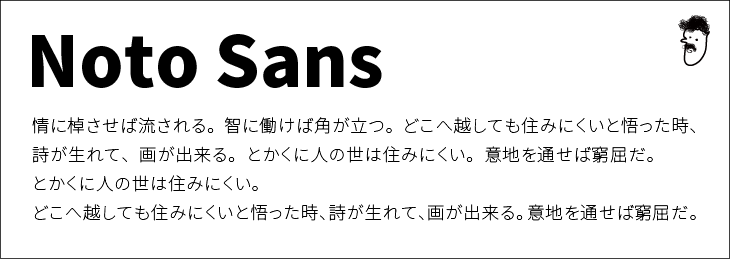
まず紹介したいのが、通常のゴシック体Noto sansです(別名:源ノ角ゴシック)
PhotoshopのアドビとGoogleが一緒に作ったフォントですね
Windowsにはメイリオ、Macにはヒラギノというキレイなゴシック体も入っていますが、Noto sansとなにが違うかと言うと
太さが7種類もある
これはデザイナーには当たり前ですが、一般の人には知られていないものすごく重要なことです
太さが7種類あるフォントだとどんなことができるか、ここから説明していきますね
ロゴの記事でも書きましたが、誰でも使える簡単で強力なテクニックの1つに「強弱をつける」というものがあります
この例を見てください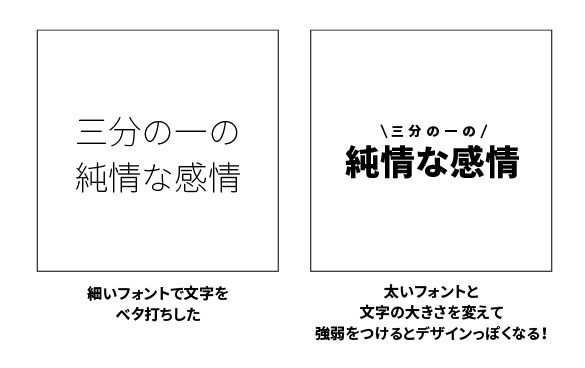
同じゴシック体でも、太さが違うとまるで別のフォントです
そしてこんなに太いフォントは最初からパソコンに入っていません
たくさんの太さがあるフォントを持つことで、表現方法が多様になりデザインの幅が広がります
▼Noto sans(ゴシック体)の使用方法
・タイトル文字
・本文
・ロゴなど文字を加工する前の骨組みとして
基本のフォントなので、何にでも使える汎用性があります、太ければ力強さを表現できるし、細いとおしゃれなデザインにも使えるマルチなフォントです
(例)
同じような文字の使い方で「力強さ」「おしゃれさ」を表現しました
・力強さを出すためには、太い文字と画像でなるべく白と黒の差を出す
・おしゃれを表現するためには余白を大事にする
ことを意識しています
▼こんなYouTubeやテレビのテロップも太いゴシックで作れます
ゴシック体の応用編
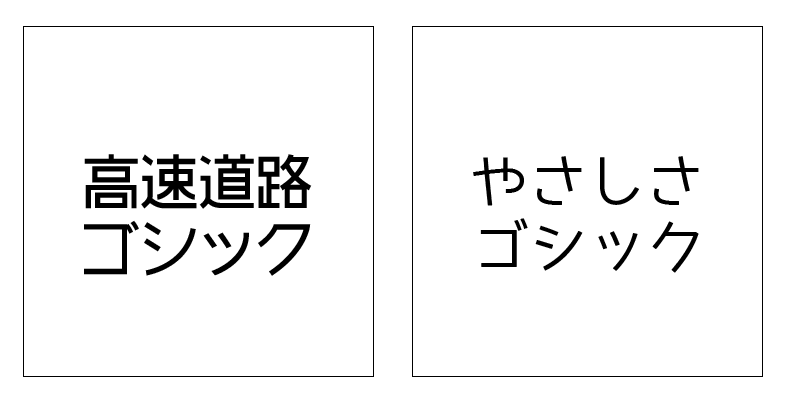
フリーフォントには他にも特徴的な楽しいゴシック体があります(太さはないけれど…)
例えば、
・高速道路ゴシック
・やさしさゴシック
こちらもゴシック体の仲間ですが、特徴的なフォントなので、使い方としては「3.デザインの質を上げる!デザイン系フォント」をご覧ください!(下の方です)
1-2 良質な明朝体
こちらで紹介するのは、ゴシック体と同様、定番のフォント「明朝体」です
紹介するフォントも、先程のGoogleとアドビが作ったフォントの明朝体バージョンです
Noto serif
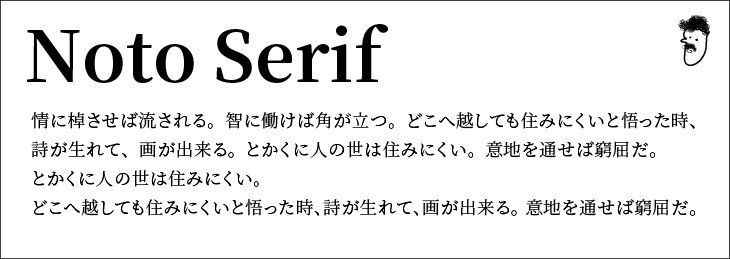
こちらも太さが7種類あるおかげで、さまざまな表現方法があります
▼Noto serif(明朝体)の使用方法
・タイトル文字
・本文
ゴシック体と違って、堅い雰囲気や、おしとやかな雰囲気を出しやすいです
新聞の文字は明朝体ですが、すべての文字がゴシック体になったら…子供向けな感じで理解しやすい雰囲気の媒体になる気がします
▼ポスターっぽい事例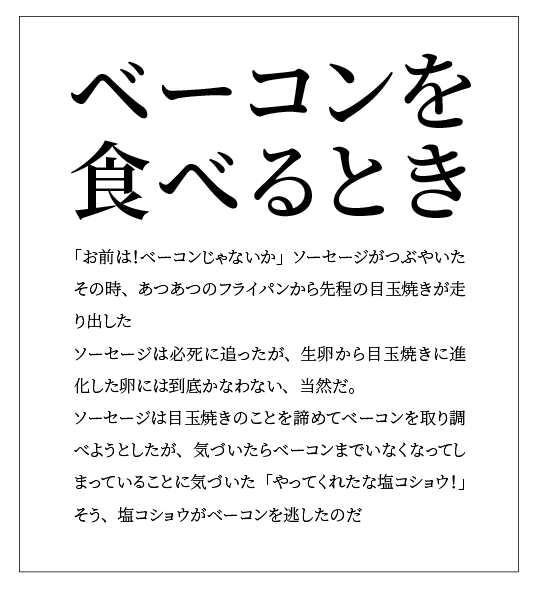
ポスターを作ってみました
・タイトルが太い明朝
・本文が細い明朝体
になっています
タイトルを細い明朝にするとこんな感じ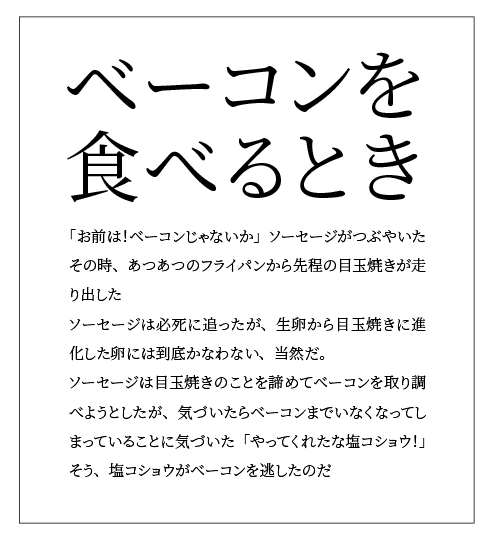
太いフォントがあると便利です
1-3 良質な丸ゴシック(フリーフォント)はコレ!
続いてみんな大好きな丸ゴシックです
源柔ゴシック
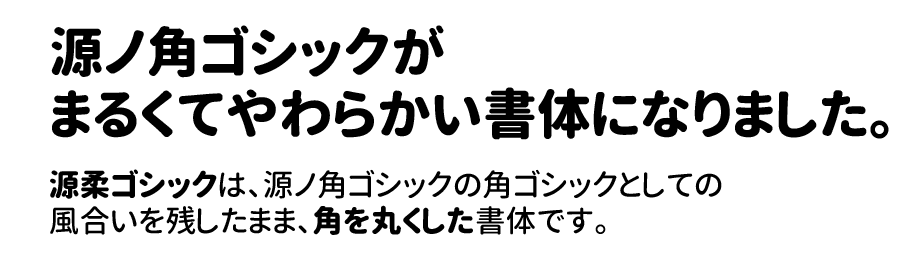
Noto sans(別名:源ノ角ゴシック)を角丸にしたフォントです
柔らかくて女性的なイメージでも使いやすいフォントです
こちらのフォントのいいところは、もうわかりますよね?
そう、太さが7種類あるところです!
さあ、ここから事例です、まずはこちら
これは、無料画像ソフトCanvaで作った画像です、文字の太さはHEAVYを使っています
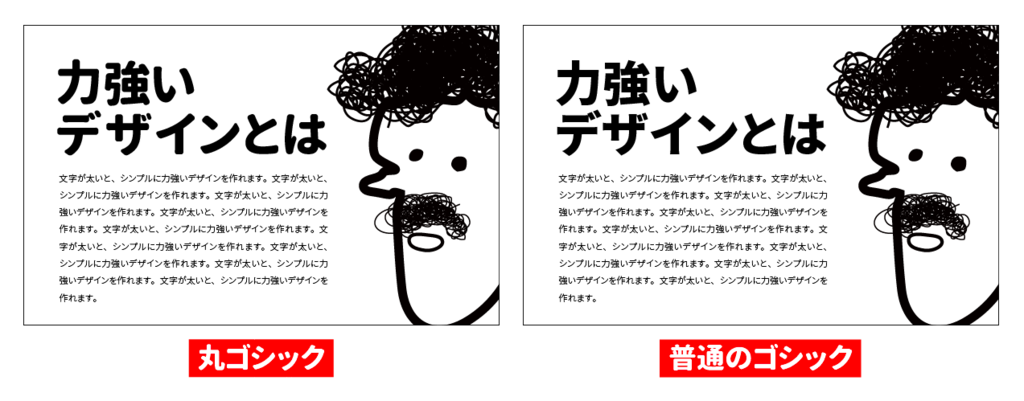
左の丸ゴシックの方が、「やさしい」イメージになったと思います
逆に右の、普通のゴシックは「力強い」ですね
どうでしょう?
柔らかさがあって、優しく語りかけるようなイメージの文字だと思います(後ろの鳥の写真ではインパクトを狙っています)
また丸ゴシック単体で見るより、普通のゴシックと比べたほうがわかりやすいと思うので比較画像を作りました
というわけで、このフォントの使いみちです
▼源柔ゴシックの使用方法
・タイトル文字(やわらかく)
・本文(やわらかく)
こちらも基本のフォントなので本文、タイトルどちらでも使われがちです
イメージとしては女性的なやわらかさを表現したり、ゴシックだと「デザインが強すぎる」でも「明朝ほどしなやかじゃない」デザインを作りたい時に使ってください
実は、最近とあるYouTuberにベーコンブログの校正を頼んで(だからクオリティが上がったのか!)、その代わりにデザインを教えているのですが、そんな彼にも「源柔ゴシックを使いなよ!」と指導しています
▼このYouTubeのサムネイルも源柔ゴシックです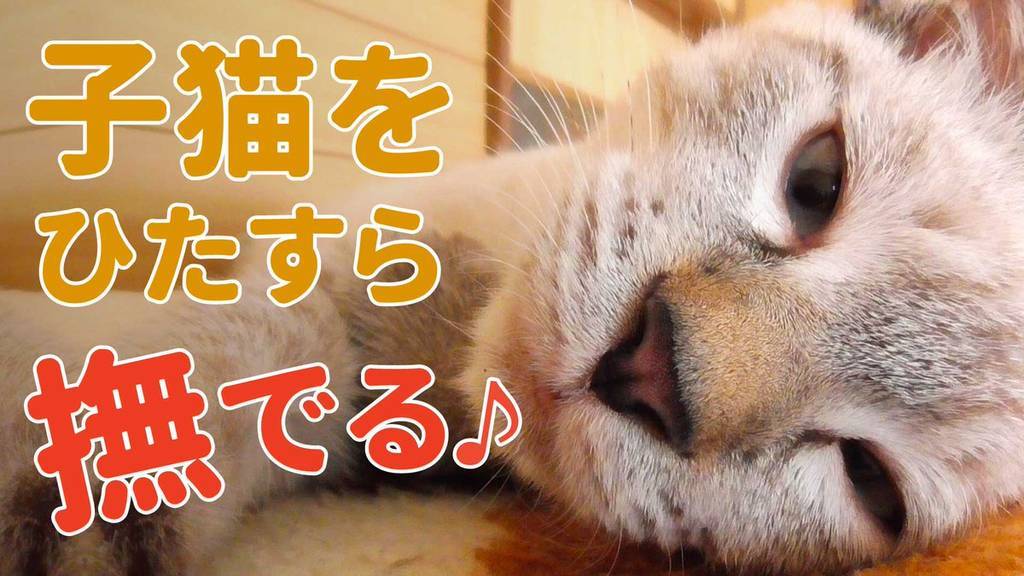
丸ゴシックは、動物関連のデザインにも合いますね
子猫の飼育チャンネルです(今見たら、全部のサムネイルに源柔ゴシック使っていました)
2. 温かみを表現できる手書きフォント
これまで紹介した、基本のゴシック体、明朝体では表現できないフォントが手書きフォントです!手書きフォントの使える場面
・子供のデザイン
・やわらかいデザイン
・堅いデザインの中のアクセントとして
・手書きのふりをする
僕もよく使います。
昔、クラウドファンディングが失敗して、支援者に向けて謝罪?の文章を作ったとき、手書きフォントを使って送りました…誠意を見せたい時にも使えます!笑(手書きが得意じゃないもので…すみません)
というわけで、僕がよく使う手書きフォントです
2-1アームド・レモン
ちなみにタイトルに使うと、こんな感じ、かなり独特な使い方です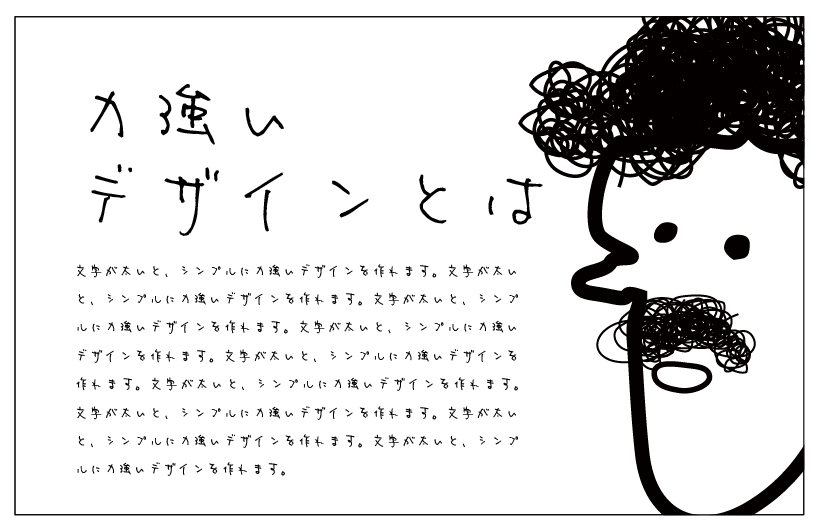
僕がおすすめの使い方はこれ
▼堅いデザインの中のアクセントとして、使います
手書きで書いた感があり、かなり注目して見てもらえます
ちなみに、このような手書きに近い手書きフォントはたくさん種類があります
ぼくのMacにはこの5つが入っていました、お好みでどうぞ!
本当に手書きっぽくしたい時は、アームド・レモンですね、えり字も結構使います
2-2殴り書きクレヨン
手書きフォントの中でも独特な、子どもがクレヨンで書いたっぽいフォントです
ポイントは、太い文字ということです
太いとロゴやタイトルに使いやすくなりますからね
▼例
ちょっと読みづらいけど、大きめの文字なら読みやすいかと思います
似た種類のフォントに「こども丸ゴシック」というものもあります
このデザインには殴り書きクレヨンの方があっていますが、「子供の文字を再現したい」けれど、デザインなのである程度読みやすくしたいというリクエストの時はこども丸ゴシックを使うことの方が多いです
2-3やまフォント
このブログで何度も紹介していますが、手書きフォントの太さがありつつ、「それぞれの文字のバランスが悪い」のがちょうどよいフォント
まとめ
以上、良質なデザインを作るため揃えるべきフリーフォントでした
デザインは練習することでうまくなります
ただ、「フォント」というデザインに必要な最低限の道具を揃えずに練習しても、うまく練習できないことがあります
デザインを練習をするためにも、今回紹介したフリーフォントを揃えてみてください
揃えずにデザインを練習するのとでは、上達のスピードが大きく変わってくるはずです